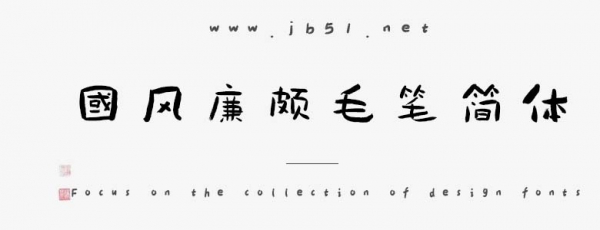
國風(fēng)廉頗毛筆簡體是一款不錯(cuò)的藝術(shù)字體,字體筆觸粗實(shí),具有很好的視覺感,適合應(yīng)用于藝術(shù)設(shè)計(jì)、平面宣傳設(shè)計(jì)、網(wǎng)頁設(shè)計(jì),書法字帖等領(lǐng)域,需要的朋友可以前來本站下載。